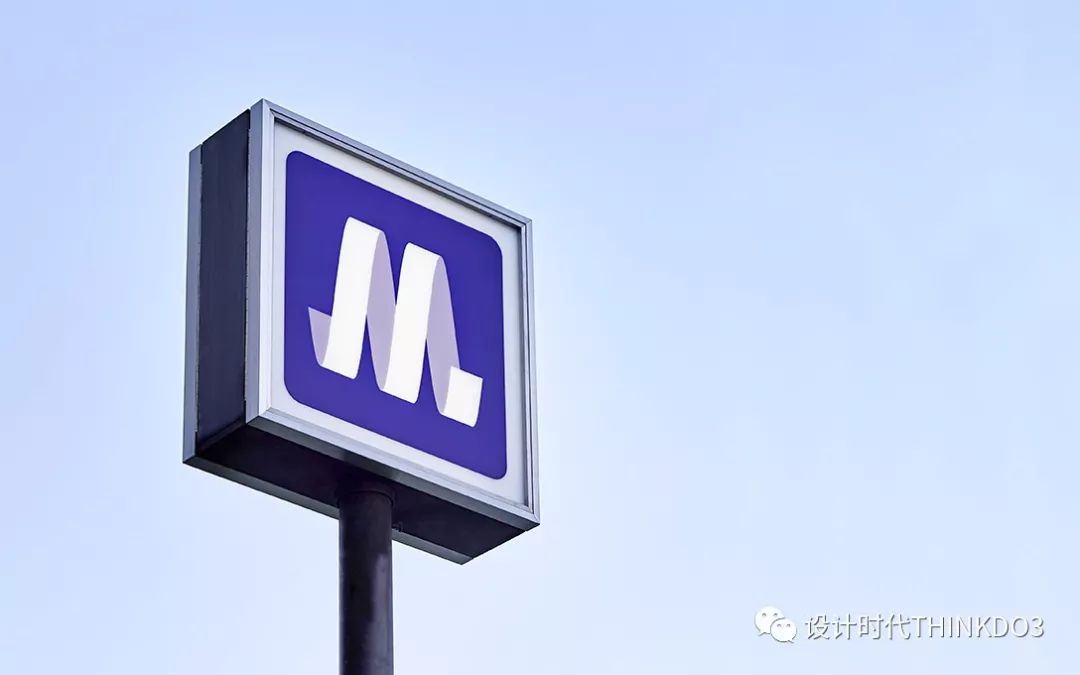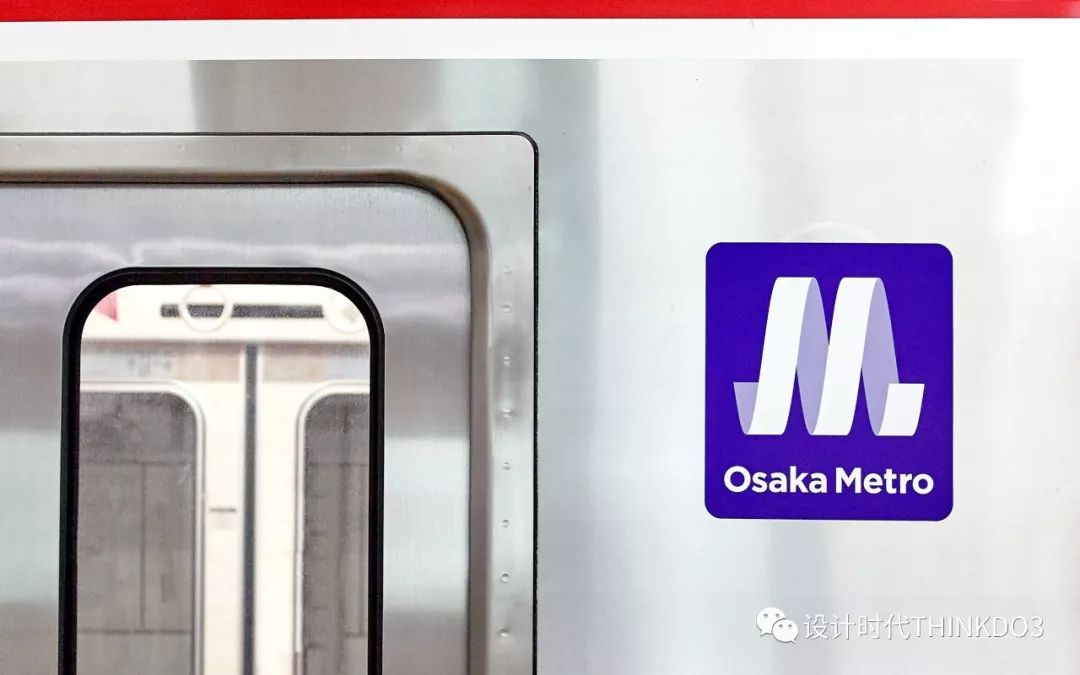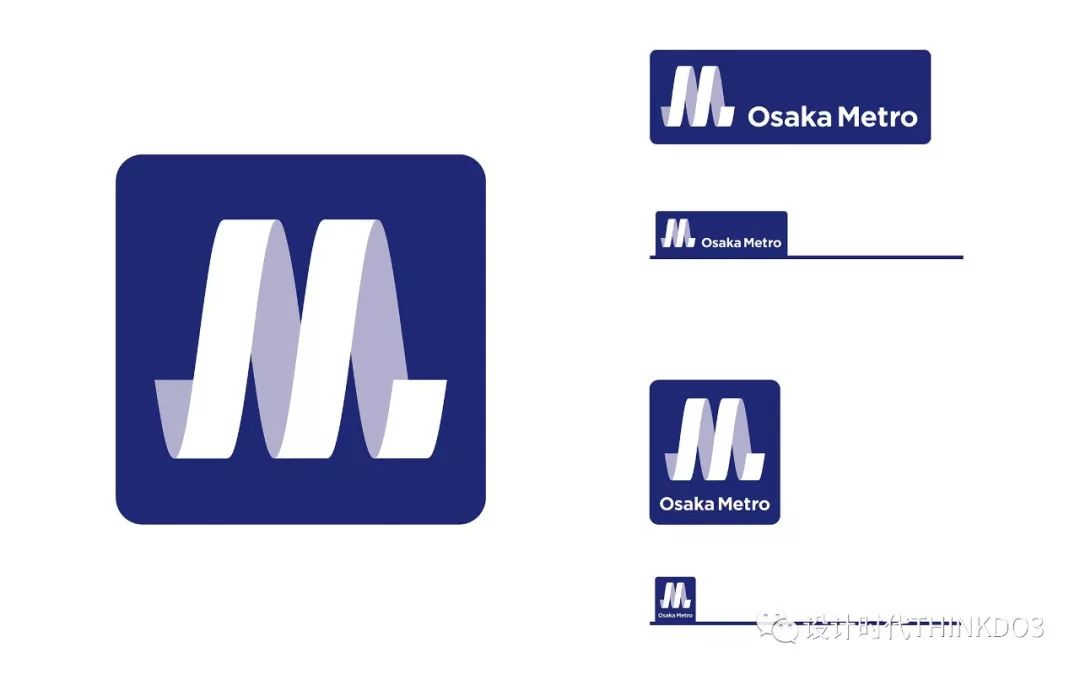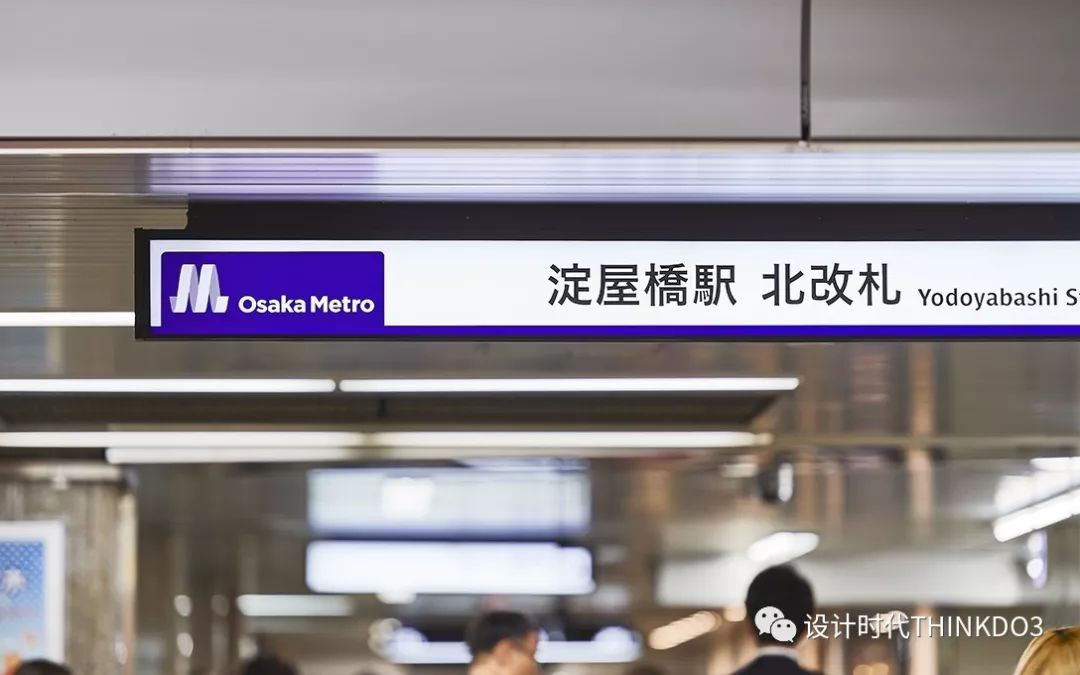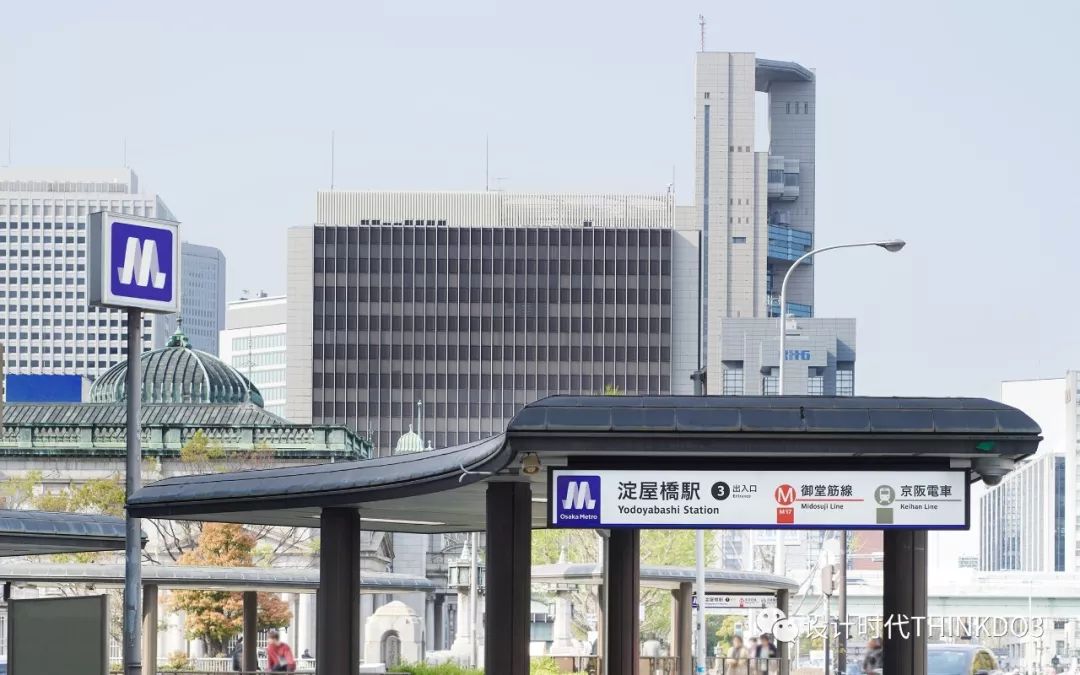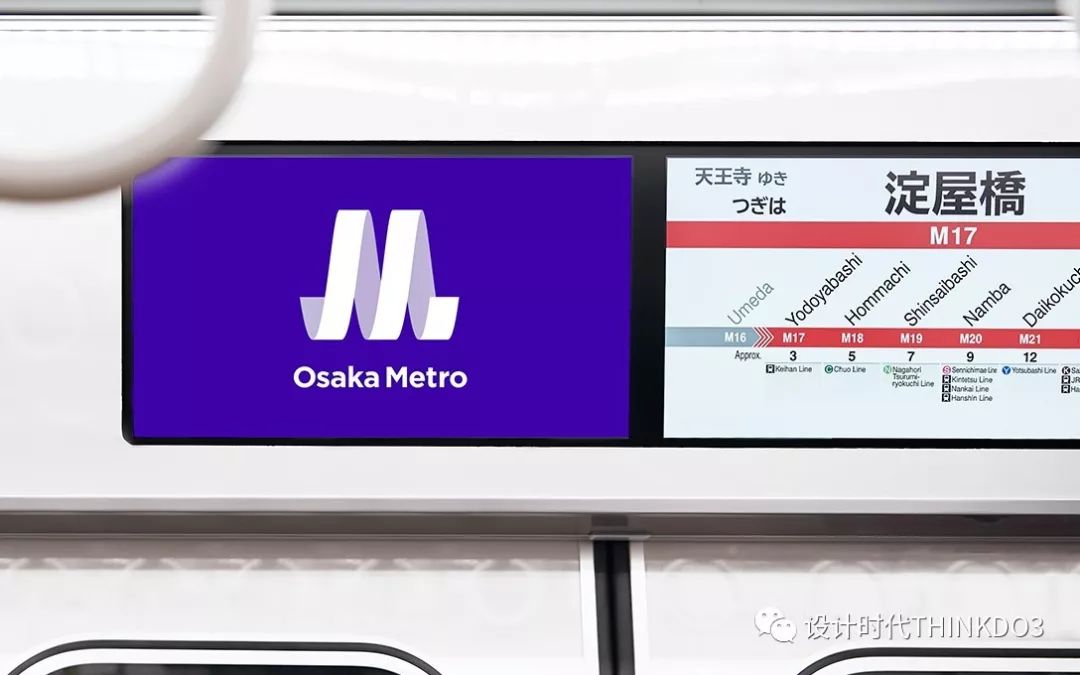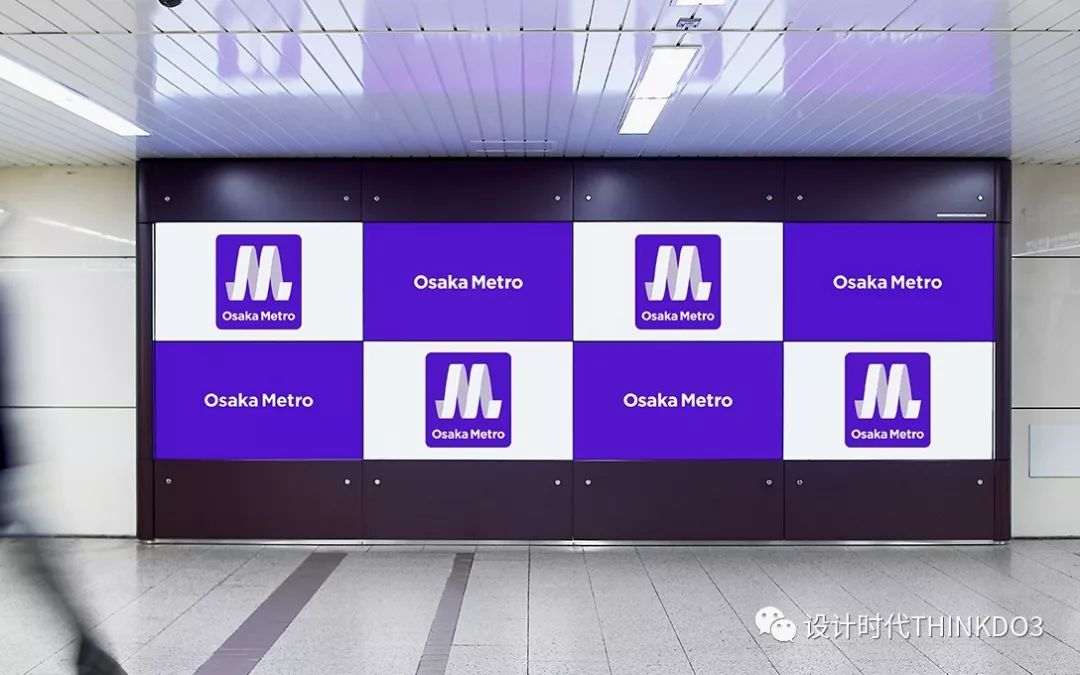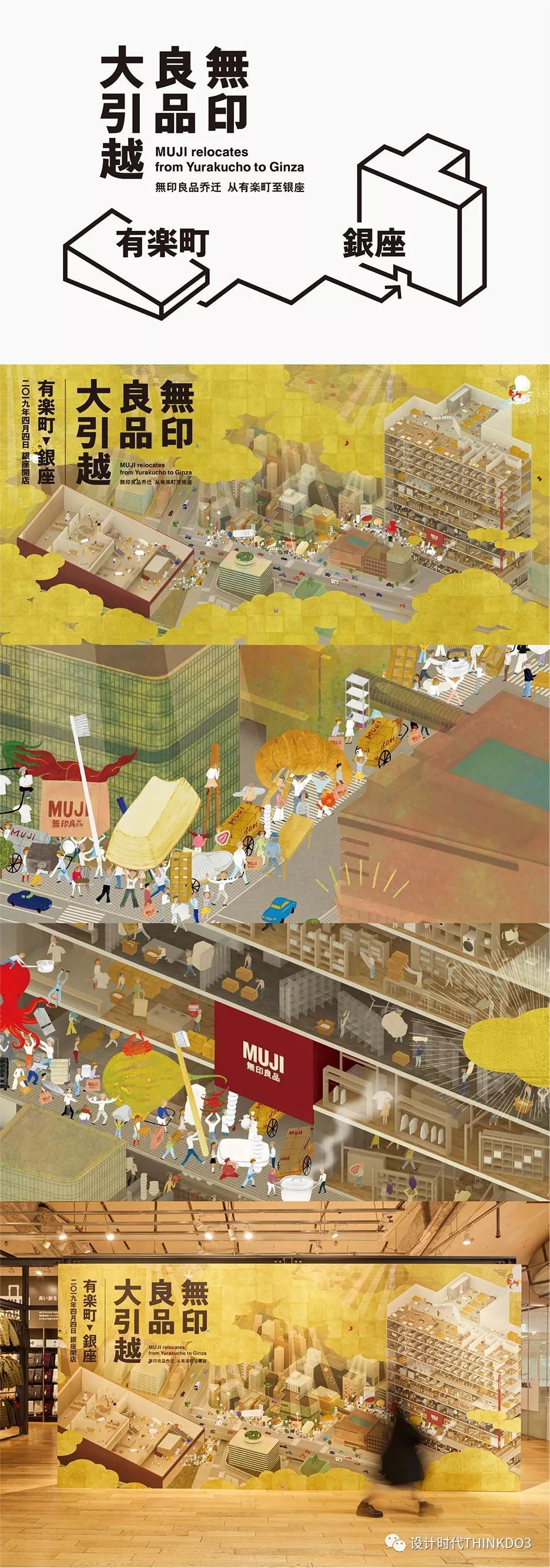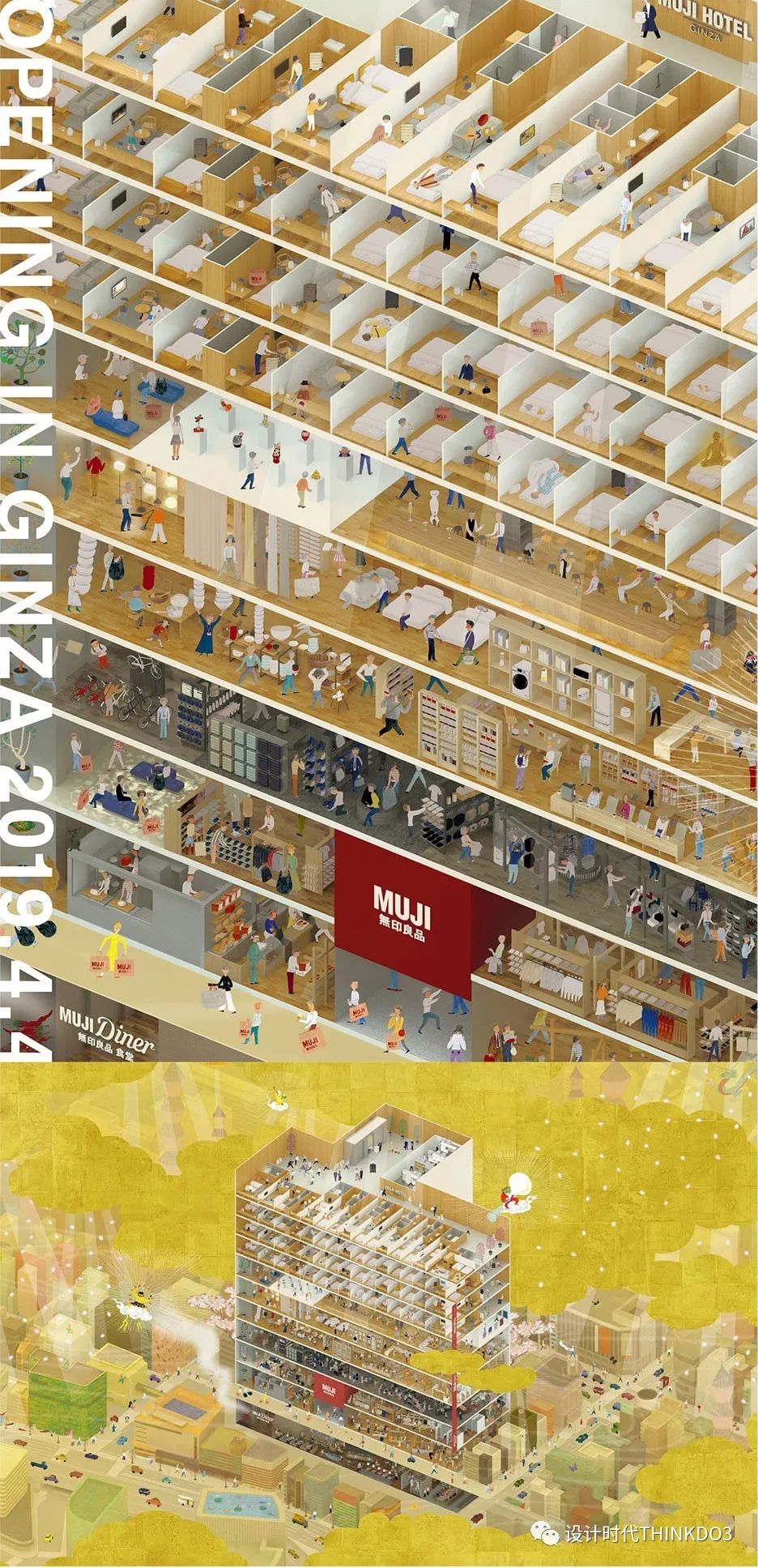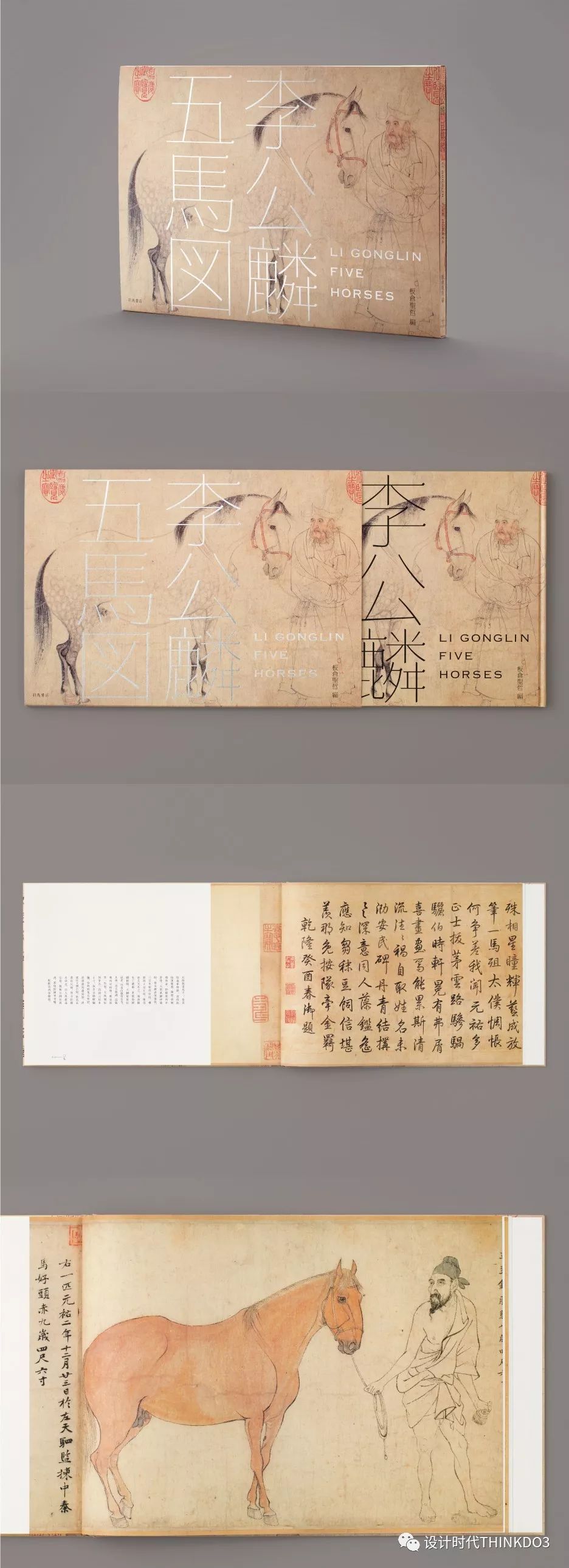
关于原研哉,
设计爱好者们再熟悉不过了
原研哉 (Kenya Hara),1958年06月11日出生于日本,日本中生代国际级平面设计大师、日本设计中心的代表、武藏野美术大学教授,无印良品(MUJI)艺术总监。
原研哉,一直活跃在设计领域,在重视 "物" 的设计的同时,还重视 "事" 的设计。
原研哉先生始终以一种不受外界影响的自在世界观去面对“日常生活”,用谦逊敏感的目光去发现设计点,然后用精准的洞察力去修正现存的设计行为理念,将现代设计推向一个更高的层次。
其设计一向遵循极简、留白、自然的风格。对于如何驾驭“地域性”和“国际性”二者的关系,原研哉回答到:“日本设计有四大特点,分别是:细致、慎重、纤细、简洁。这四点渗透到了日本的方方面面。越是质朴到极致的东西,越是高级感更足,这种‘周到的精细’在设计中是非常有价值的。”
“设计是一种教养”,原研哉,说出在他心中设计的定位,他认为“设计师”不该是社会中特殊的行业,设计更不该让人难以亲近,设计品也不仅是“礼品”。设计应该是一种教养,就像是公德心、礼貌般,是能随时挂在嘴边,是能环绕在日常生活之中,是能无声无息影响着人们的生活的。
Osaka Metro 大阪地铁VI视觉设计
由公营转为民营、重新开业的“大阪地铁”的VI规划。
其象征图案反映了同样用于企业口号的品牌概念–“不断行进,不断变化”。通过内含地铁“Metro”的“M”,以及大阪“Osaka”的“O”的螺旋动感形态(活动M),体现出充满活力的大阪街巷,以及不断行进的生命力。
ISETAN DOOR定期送货服务品牌视觉设计
LOGO中“DOOR”的“OO”好比具有高度鉴别力的百货商店采购员的“眼睛”,表达方式让人感到亲切。送货的快递箱上也变形绘出“眼睛”的表情,既简洁明快,融合于生活,又富有新意。
SICF19 艺术节品牌视觉设计
“SICF19”以发掘、培养、支持年轻创作者为目的的艺术节品牌
灵感以“发掘原石”为理念,
来制作LOGO、VI工具、动画和奖杯
韩华保险子公司“LifePlus”品牌新形象设计
LifePlus成立于2017年,是由韩华生命、韩华损害保险、韩华投资证券、韩华资产运用和韩华储蓄银行6家韩华集团金融子公司联合创建的以面向生活服务的金融品牌。
LifePlus全新的标识让人联想起我们的生活,从“固定”到“移动”的扩展,形成一种有机变化和成长的生活方式,将现代人的生活融入Life Plus品牌价值中,并期望能够改变人们的生活并得到积极的发展。
草间弥生美术馆 视觉识别设计
从前卫艺术家草间弥生的亲笔签名中获得灵感,设计出的视觉识别。已应用于宣传册、开馆纪念展宣传单页、名片和信封。
采用富有特色的人类形象图形,使参观者能直观理解单向行进路线,可顺利参观馆内各处。
充分利用视觉识别和草间作品的要素,应用于美术馆原创商品的包装、工作人员T恤等。
草间弥生美术馆开馆纪念展的展品目录。封面采用将作品贴在质感明显的粗涩材质上的设计,再加以黑色和银色的烫金处理等,打造出富有质感的目录。
MUJI无印良品全球最大门店
这些插图广泛应用于火车上的数字标牌和网页横幅广告中。主要通过火车、公共汽车和其他交通系统和标牌上的广告推广无印良品。(详细请看往期介绍链接)
無印良品イオンモール堺北花田
为世界上最大的无印良品商店制定了视觉;它的特点是拥有无印良品首家大型食品卖场。该标牌在商店中分为两种颜色,正常销售区为深红色,灰色用于食品部分。
Minamiza京都剧院新视觉设计
高松市美术馆VI视觉设计
位于香川县的高松市美术馆的VI规划。
象征图案是将“Takamatsu Art Museum”的首字母比作高松的街景与浮现在濑户内海的岛屿。与馆名徽标组合而成的签名,则是考虑了近景、远景等在濑户内海航行的船上所观望到的景致,设计出多种变化。
ローチケ罗森票务品牌形象设计
“ロ”既可理解为人的笑口,也可理解成舞台、会场的形状。
通过象征性的表现,形成与娱乐活动相符、灵活性强的徽标。
MIKIMOTO日本珠宝商品牌VI视觉设计
在赋予标识以正体所应有品格的同时又行整理,使其兼备现代性与清晰度。品牌色为“未成之白”–换而言之,即将其设置为功成圆满前具有可能性的“白”,通过运作富于变化的“白”而进行呈现。
椿山庄三重塔 动工仪式法事
三重塔是象征椿山庄的历史性建筑。
这是其平成大改建动工仪式法事的美术指导。
标志以象征性的的三个屋顶为主题,标志风格美丽端正,在设计上都是探寻历史和现代最合适的融汇点,用最小要素衬托出椿山庄的造型美。
堂岛酿酒所包装设计
堂岛酿酒所是一家酿酒公司,在英国剑桥郊外原属于庄园领主的“Fordham Abbey”城堡内酿酒。业务内容全面,涵盖从产品包装到品牌加速的全套业务。
Oven the Dish 产品包装
用于烤箱加热的冷冻食品的包装设计。“只需烤箱加热,就能在家享用正宗的宴会大餐”,用美食和人的温馨图片展现这一理念。摆在店铺的货架上,突出了3种产品的系列感和易识别感。
燃烧吧!辣椒 休闲食品包装设计
原材料为辣椒,可尽享辣味的休闲食品包装。通过红、白两个基本色的明快结构,简洁地体现出品味“辣”的这一商品性。
丽唯特丙烯水粉画 颜料包装设计
这是一款丙烯水粉画颜料的包装设计,具有不透明、整体打造为亚光的特征。
通过使颜料从丽唯特的徽标上滴落,体现出颜料的特征。利用显示颜色明亮程度的数值(VALUE)将颜色的表达设定为使形状发生变化的机制,从而形成犹如与创作活动产生亲和的动态包装款式。
Okhotsk Okoppe有机牛乳品牌包装设计
设计捕捉到一头可爱的奶牛站在一片纯白的雪地里,这是北平原农场的独特风貌。这象征性地表达了品牌严肃的态度和诚实的工艺。
Genichiro Inokuma’s Toy Box书籍设计
日本具有代表性的画家–Genichiro Inokuma的作品集。
通过在世界各地收集的精美藏品,表达出Genichiro Inokuma对待客体的方式与视点。“美好的生活方式”是什么?一册充满Genichiro Inokuma魅力的作品集,只需翻看就会变得快活、开心。
Li Gonglin—Five Horses书籍设计
YOSUI BOX《100个白人》新书
La Seine Musicale导视设计
位于巴黎郊外赛甘岛上的音乐复合设施的VI与标识规划。象征图案为抽象化的建筑造型,在建筑物内部起着显示各项设施场所的功能。标识规划则是在类似五线谱的条格上配置文字及箭头,使信息漂浮于空间。